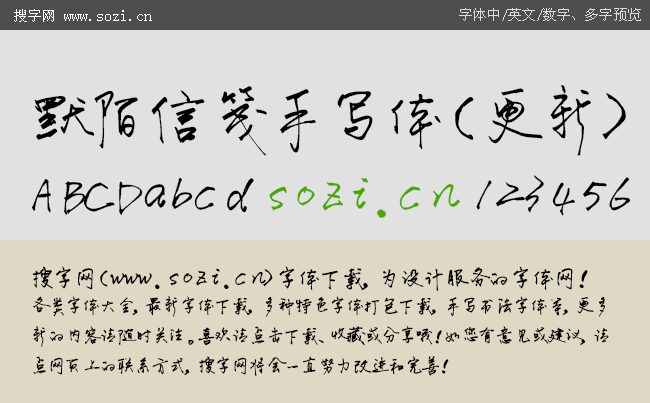
默陌信箋手寫體(更新)
搜字網(wǎng)提供一款默陌信箋手寫體(更新)手寫中文書法字體下載,默陌信箋手寫體是一款適合信箋明信片等應(yīng)用的手寫字體,字體大小擁有豐富的變化,位置有所偏倚,輸入時字體視覺上會錯落開來,書寫效果更貼近真實的,能夠應(yīng)用于平面設(shè)計、名片設(shè)計、廣告創(chuàng)意、印刷等場合應(yīng)用。